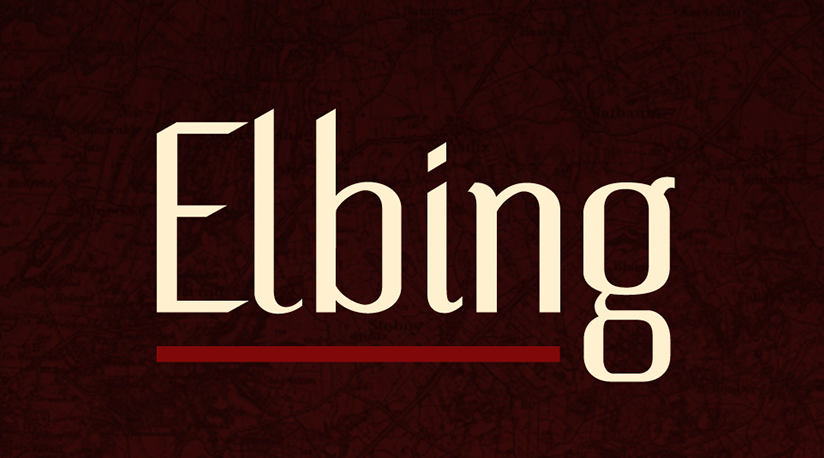
Aqui está uma descrição envolvente para a página de download da font ‘Elbing Font’, que mantém a essência do texto fornecido: A font Elbing é um design cuidadosamente desenvolvido pelo designer Mateusz Sztajnke, disponível gratuitamente. Este tipo de letra sans-serif é perfeitamente adaptada para uso em diversas plataformas digitais e impressas, desde materiais comerciais até aquelas destinadas a projetos pessoais ou educacionais. Você pode usá-la livremente em qualquer publicação digital ou impressa sem preocupações legais. O melhor de tudo, você não só pode usar Elbing para suas próprias necessidades, como também distribuí-la gratuitamente aos amigos e colegas que possam estar em busca de uma alternativa moderna e elegante. O fato é que a font contém um arquivo informativo, o que significa que, sempre que compartilhar sua versão com terceiros, mantenha esse arquivo junto ao conjunto do tipo-fonte. Este detalhe garante que os usuários recebam toda a informação necessária para usar e aplicar de maneira correta a font Elbing em suas produções. Com um design limpo e minimalista, a Elbing oferece uma opção versátil para qualquer projeto gráfico ou layout digital. Não importa se você estiver criando elementos de marca, textos profissionais, logotipos, infográficos ou páginas web: a font Elbing está aqui para ajudar a dar vida e um toque diferenciado a seu trabalho.